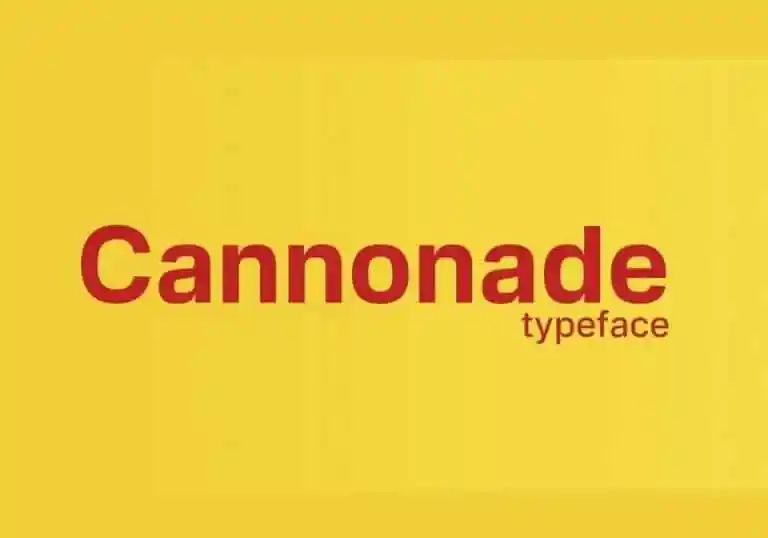
A Cannonade Sans Serif Font é uma criação moderna do designer Camille Khubbetdinov, adaptada para atender a uma variedade de necessidades digitais. Com seu formato sem serifos distintivo e elegante, esta fonte proporciona um contraste sofisticado que se destaca em qualquer layout ou aplicativo digital. A Cannonade mantém uma aparência firme e simples ao mesmo tempo, tornando-a perfeita para uso em mobile apps, websites e revistas. Seu formato quadrado facilita a leitura em telas pequenas, garantindo um visual claramente legível mesmo sob condições de luz variáveis. Combinar esta fonte com outros recursos gráficos modernos criará uma experiência de interação amigável e imediata para seus usuários. Engaje seu público-alvo com a Cannonade Sans Serif Font: uma solução versátil que oferece estilo, precisão e facilidade de leitura no formato sem serifos.